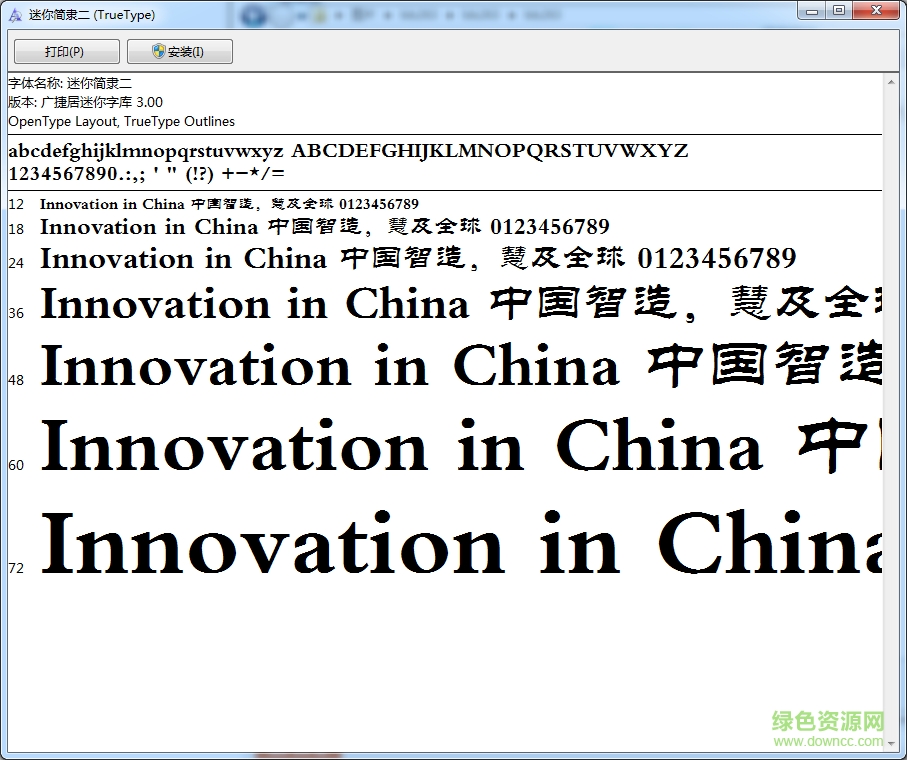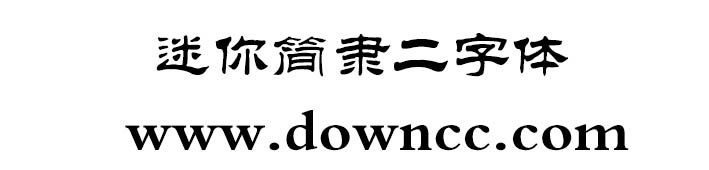
迷你簡(jiǎn)隸二是一款簡(jiǎn)潔大方的電腦字體軟件,字體端莊高雅重點(diǎn)突出,使用便捷在設(shè)計(jì)中彰顯個(gè)性??靵?lái)綠色資源網(wǎng)下載體驗(yàn)吧!
迷你簡(jiǎn)隸二源自于鉛字銅模字,字體結(jié)構(gòu)嚴(yán)謹(jǐn)端正,有濃厚的藝術(shù)底蘊(yùn),可用于書(shū)籍、報(bào)紙、廣告宣傳、招牌等。